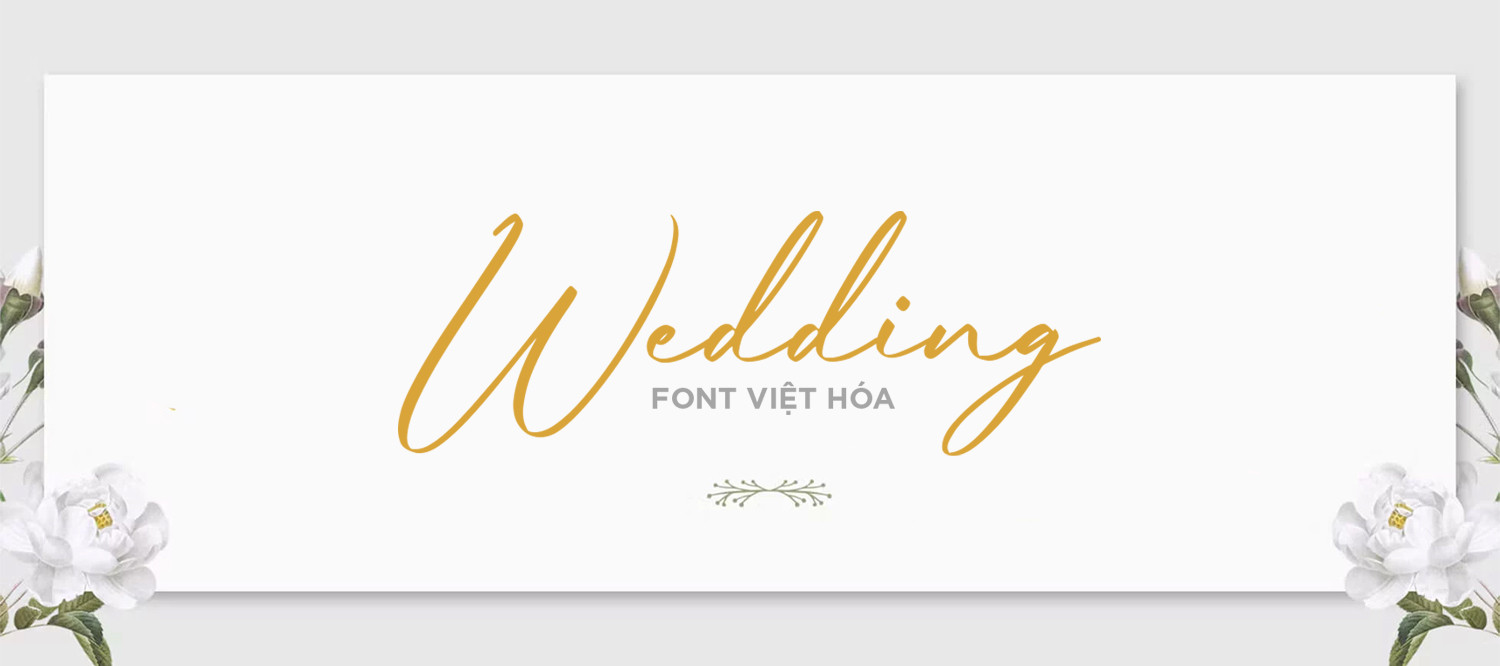
[Tải xuống] TOP 15 Font Chữ Đám Cưới Việt Hóa Đẹp Nhất 2025
Ngày cưới là một sự kiện trọng đại, và mỗi chi tiết nhỏ trong ngày này đều quan trọng, bao gồm cả thiết kế thiệp cưới. Trong đó, việc chọn lựa font chữ đám cưới cũng không kém phần quan trọng. Font chữ không chỉ là công cụ truyền tải thông điệp mà còn tạo nên không khí và dấu ấn đặc biệt cho ngày lễ trọng đại này. Trong bài viết này, chúng tôi sẽ giới thiệu TOP 15 font chữ đám cưới Việt hóa đẹp nhất 2025, giúp bạn chọn lựa những kiểu chữ phù hợp để làm nổi bật sự kiện quan trọng nhất trong cuộc đời.
Giới thiệu về Font Chữ Đám Cưới
Font chữ đám cưới có ảnh hưởng lớn đến phong cách và cảm xúc của thiệp cưới cũng như các sản phẩm liên quan như banner, bảng chỉ dẫn, và thiệp cảm ơn. Việc chọn lựa một font chữ phù hợp không chỉ giúp thiệp cưới của bạn trở nên đẹp mắt mà còn thể hiện được phong cách cá nhân và chủ đề của buổi lễ.
Top 15 Font Chữ Đám Cưới Việt Hóa Đẹp Nhất 2025
Font Chữ Việt Hóa Sang Trọng Cho Thiệp Cưới
Font Chữ Sang Trọng và Hiện Đại TH Luxury 6
Font chữ TH Luxury 6 mang đến phong cách hiện đại, nhưng vẫn không kém phần sang trọng. Với các đường nét thẳng và đều, font chữ này hoàn hảo cho những thiệp cưới mang phong cách thanh lịch, hiện đại nhưng vẫn đầy đẳng cấp.
Font Chữ Spa, Thẩm Mỹ Đẹp TH Luxury 7
Font TH Luxury 7 có thiết kế mềm mại, nhẹ nhàng nhưng không thiếu sự sang trọng. Với các nét uốn lượn tinh tế, font chữ này rất thích hợp cho các đám cưới theo phong cách thư giãn, sang trọng và hiện đại.
Font Chữ Serif Nét Mạnh Sang Trọng TH Luxury 5
Font chữ TH Luxury 5 với các đường nét mạnh mẽ, sắc sảo mang đến vẻ đẹp quyền lực và lịch lãm. Đây là lựa chọn lý tưởng cho những đám cưới mang phong cách trang trọng, cổ điển và đầy tinh tế.
Font Chữ Viết Tay Lãng Mạn Cho Đám Cưới
Font Ký Viết Tay Viết Hóa TH Molahesta Italic
TH Molahesta Italic là font chữ viết tay lãng mạn, mang lại sự nhẹ nhàng và mềm mại. Những đường cong uyển chuyển của nó rất phù hợp với các thiệp cưới mang phong cách cổ điển, lãng mạn.
Font Ký Viết Tay Viết Hóa TH Modernline
Font TH Modernline có các nét uốn lượn mượt mà, mang lại cảm giác gần gũi và chân thành. Đây là lựa chọn lý tưởng cho những cặp đôi yêu thích sự hiện đại nhưng vẫn muốn giữ lại sự lãng mạn trong ngày trọng đại.
Font Viết Tay Nét Mạnh Mềm Mại TH Viettay 4
TH Viettay là font chữ kết hợp giữa nét mạnh mẽ và sự mềm mại, tạo nên một phong cách độc đáo, vừa mạnh mẽ nhưng cũng rất tình cảm. Font này rất phù hợp cho những thiệp cưới vừa truyền tải sự chân thành lại vẫn đầy sự kiên định.
Font Ký Viết Tay Handwriting Bibliophile Script
Bibliophile Script mang đến sự tự nhiên và thanh thoát, với các đường nét mềm mại và uốn lượn. Font này thích hợp cho các đám cưới theo phong cách giản dị, nhẹ nhàng, nhưng vẫn đầy lãng mạn.
Font Ký Hiện Đại TH Histerm
TH Histerm là font chữ viết tay hiện đại với những đường nét sắc bén và chắc chắn, nhưng vẫn giữ được nét tự nhiên và mềm mại của chữ viết tay. Đây là sự lựa chọn tuyệt vời cho các thiệp cưới mang hơi hướng hiện đại, sáng tạo nhưng vẫn ấm áp.
Font Chữ Viết Tay Mềm Mại TH Migratory
TH Migratory có nét chữ mềm mại, dịu dàng, dễ dàng truyền tải cảm xúc và tạo ra không khí lãng mạn cho ngày cưới. Với những đường cong mượt mà, font này phù hợp cho các thiết kế thiệp cưới nhẹ nhàng và thanh thoát.
Font Chữ Mềm Mại TH Milyah
TH Milyah mang đến một cảm giác gần gũi và dễ chịu, những nét chữ dịu dàng giúp tạo nên sự ấm áp, nhẹ nhàng cho thiệp cưới. Đây là font chữ tuyệt vời cho các cặp đôi yêu thích sự tinh tế và mềm mại.
Font Chữ Cổ Điển và Retro
Font Chữ Sang Trọng TH Honest Proud
TH Honest Proud mang đến vẻ đẹp cổ điển, sang trọng với các đường nét mạnh mẽ và đầy tính biểu cảm. Font này rất phù hợp cho những đám cưới theo phong cách cổ điển, sang trọng và quý phái.
Font Chữ Cổ Điển Viết Hóa TH Hustle Culture
TH Hustle Culture là font chữ mang đậm phong cách cổ điển và hiện đại. Với những đường nét mạnh mẽ nhưng vẫn mềm mại, font này là sự lựa chọn hoàn hảo cho những đám cưới kết hợp giữa nét cổ điển và sự trẻ trung, năng động.
Font Chữ Cổ Điển Nét Mạnh TH Hildesheim
TH Hildesheim mang đến một phong cách cổ điển, chắc chắn và đầy tinh tế. Font này rất phù hợp với các đám cưới mang phong cách quý tộc, cần thể hiện sự sang trọng và quyền lực.
Kết Luận
Việc chọn lựa font chữ cho thiệp cưới là một phần quan trọng trong việc tạo nên một đám cưới hoàn hảo. Chọn font chữ phù hợp không chỉ giúp thiệp cưới đẹp hơn mà còn thể hiện được phong cách và cá tính của cặp đôi. Hãy chọn những font chữ Việt hóa đẹp nhất 2025 và biến ngày cưới của bạn trở nên thật đặc biệt!